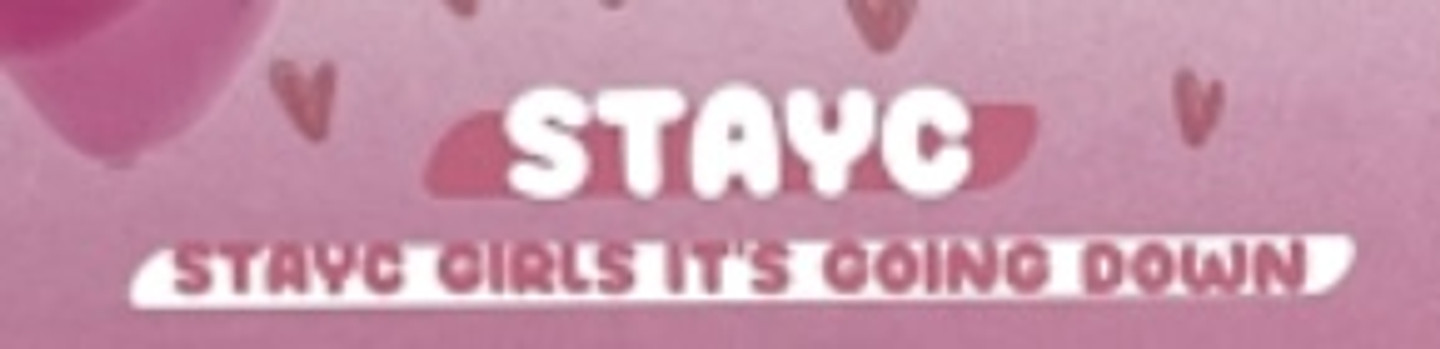
어떤 폰트인지 아시는 분 계실까요? 꼭 저 폰트 아니더라도 저런 느낌으로 둥글둥글한 폰트 아시는 분 계시면 알려주세요ㅜㅜ
산돌 오동통
저 폰트가 산돌 오동통체로 보이진 않지만 비슷한 폰트라 한 번 써봅니당. 눈누엔 없습니다만 시간이 많이 지나서 이미 찾으셨을지도 모르겠네요